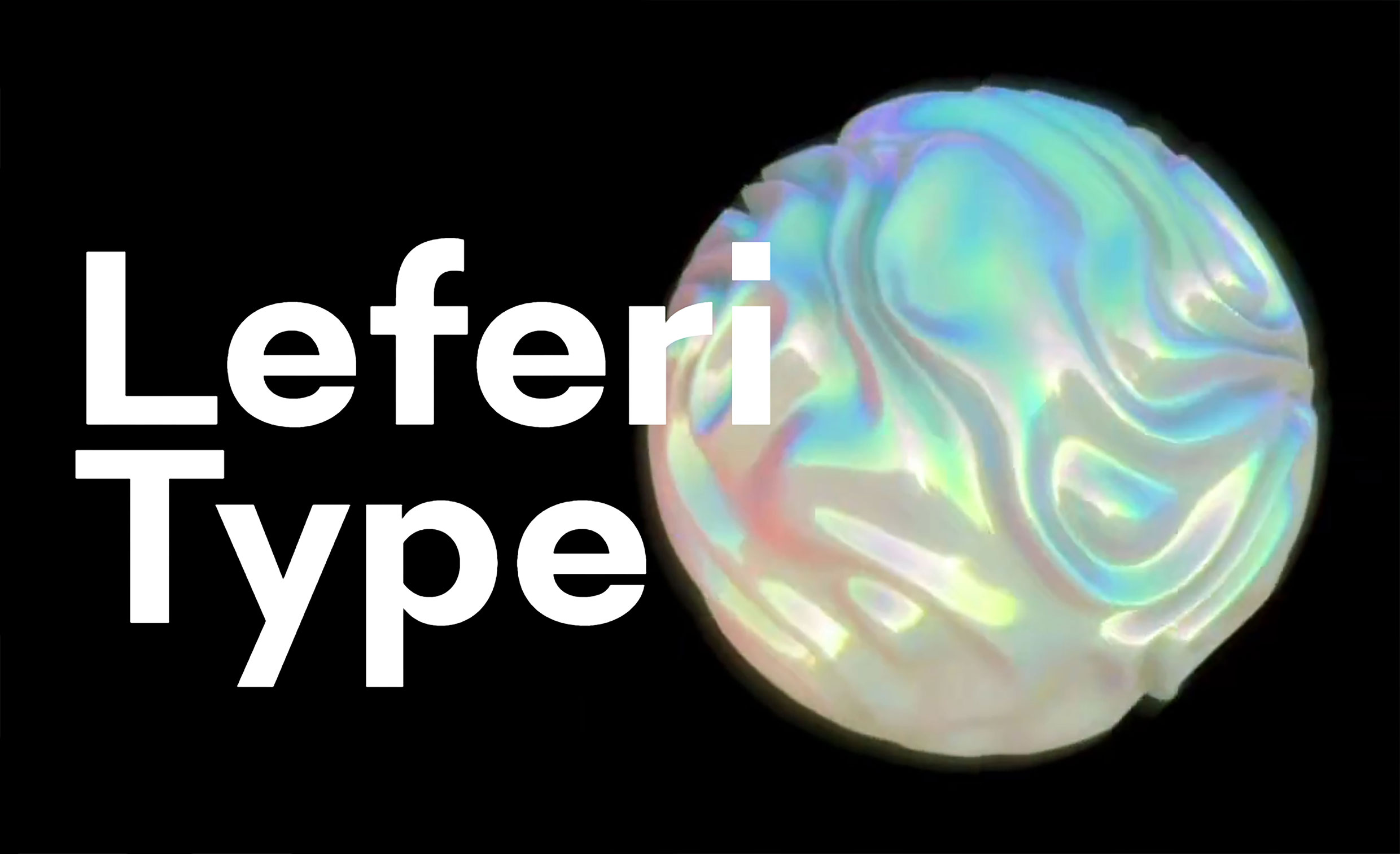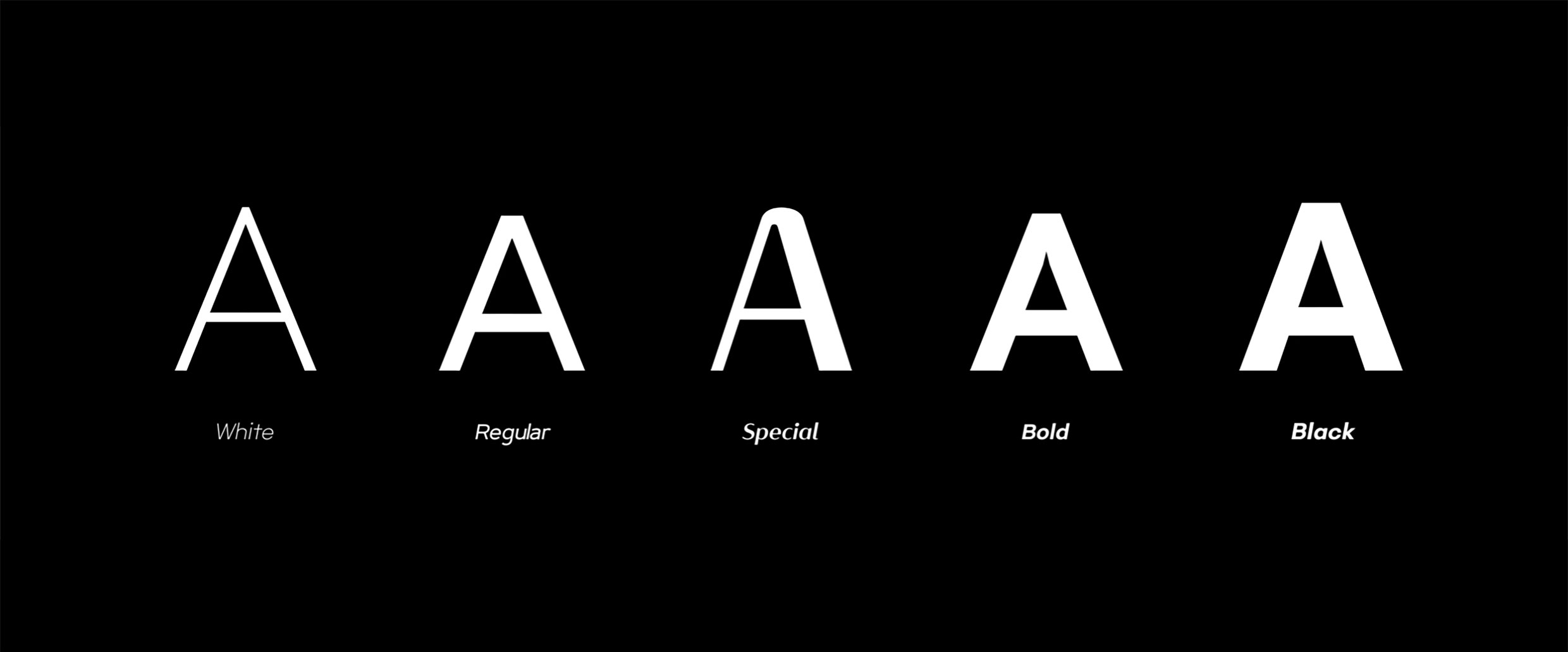
레페리, 윤디자인과 함께 레페리타입 서체 8종 공개
뷰티 인플루언서 비즈니스 그룹 ‘레페리’는 한글 개발 및 타이포브랜딩 전문기업 (주)윤디자인 그룹과의 협업을 통해 개발한 레페리타입(Leferi Type) 서체 8종을 공개하고 무료로 배포한다고 15일 밝혔다. 이번 프로젝트는 레페리가 추구하는 인문학적 가치와 기업의 본질을 서체에 담아 공유함으로써 구성원과 크리에이터, 그리고 사회와 소통할 수 있는 계기를 만들고자 진행됐다.
레페리에서 선보인 Leferi Type은 단합과 확장, 그리고 창조적 가치를 상징하는 레페리의 심볼 프리즘(Prism)에서 모티브를 얻어 제작됐다.
빛이 프리즘을 통과하면서 단편적인 형태로 존재하지 않고 다양한 줄기로 퍼져 나가듯이 레페리 구성원들과 크리에이터들 역시 세상에 얽매이지 않고 자유롭게 도전을 즐기며 최초, 최고, 유일의 가치를 창출한다는 의미를 담았다.
Leferi Type은 ‘베이스 타입(Base Type)’과 ‘포인트 타입(Point Type)’ 2가지 형태로 개발됐다. 일반적으로 사용하는 제목용, 본문용이 아닌
뷰티 영역에 특화된 비즈니스의 특징을 드러낼 수 있도록 메이크업 용어를 차용해 ‘포인트 타입’과 ‘베이스 타입’으로 서체명을 정했다. 각각의 서체를 일렬로 배열 시 프리즘에서 빛이 확장되는 이미지를 연출해 디자인적 심미감을 높였다. 특히 ‘Special 서체’는 한줄기의 빛이 프리즘을 통해 뻗어 나가는 모습을 디자인적으로 구현함으로써 레페리의 도전정신을 직접적으로 나타냈다.
또, 사용 목적에 맞게 서체를 유동적으로 적용할 수 있도록 굵기뿐만 아니라 세밀한 형태적 특징을 포인트로 주어 활용성을 높였다. 영문의 경우 ‘포인트 타입’은 지오메트릭 산스(Geometric Sans)기반의 정교하고 깔끔한 형태의 디자인으로 적용해 제목 서체로 사용 시 주목도를 높일 수 있으며, ‘베이스 타입’은 일부 자소를 판독성이 높고 안정적인 형태로 구현해 작은 크기에서도 커뮤니케이션이 용이하도록 도왔다.
최인석 레페리 대표는 “서체는 기업 정신을 나타내는 상징물이자 생각과 이념을 나누는 표현 수단이다”라며 “Leferi Type에 레페리가 추구하는 자유와 도전정신, 핵심 가치들을 시각적으로 구현시킴으로써 세상에 레페리의 본질적 가치를 소개하고 새로운 인연을 맺을 수 있는 기회의 도구가 되길 기대한다”고 전했다.